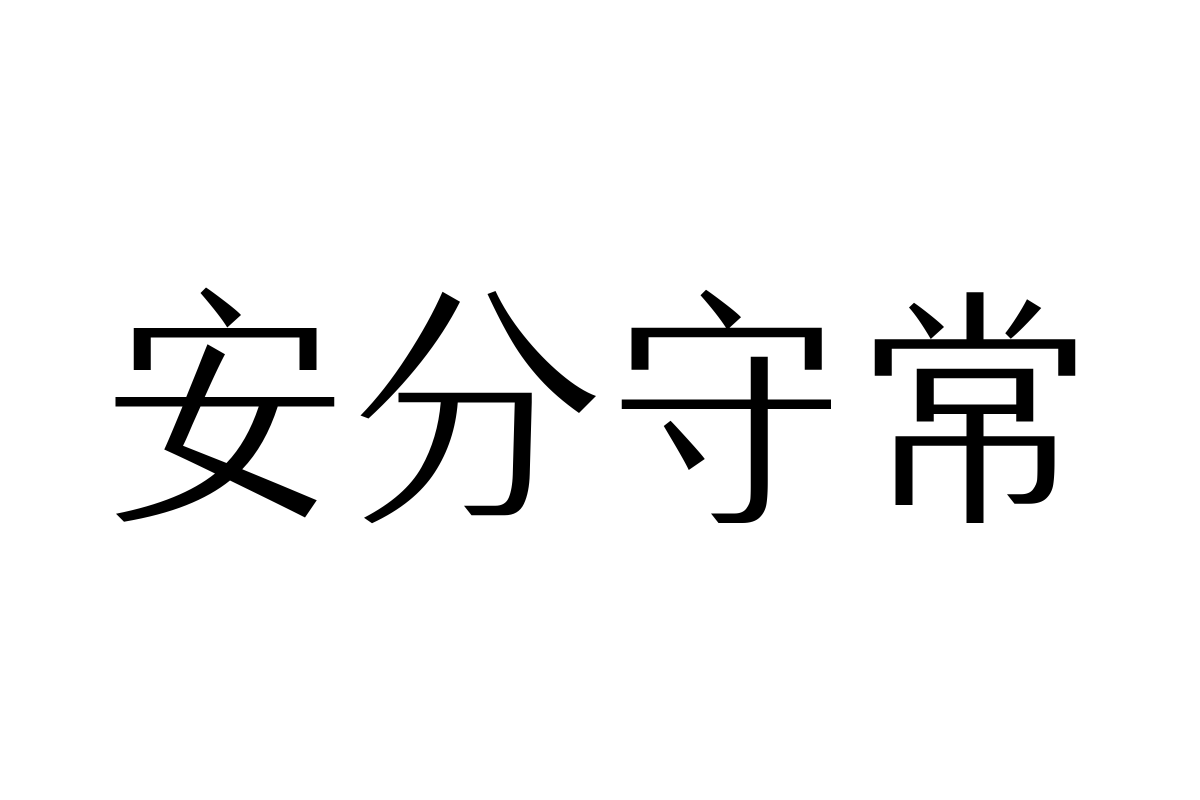
三极翰林简体字体是一款具有独特风格的中文字体,它采用了现代的设计元素,使得整体视觉效果更加简洁、大方。这款字体的特点主要体现在以下几个方面:
1. 字形优美:三极翰林简体字体的字形线条流畅,结构紧凑,给人一种优雅的感觉。无论是书写还是阅读,都能让人感受到一种舒适和愉悦。
2. 易于识别:这款字体的笔画粗细适中,易于识别,不会因为过于复杂而影响阅读效果。同时,它也具有一定的可读性,适合用于各种印刷品和电子屏幕上的展示。
3. 适用范围广泛:三极翰林简体字体适用于各种场合,无论是正式的文件、报告,还是日常的笔记、日记,都能轻松驾驭。它的设计既符合商务场合的需求,也能满足个人使用的需求。
总的来说,三极翰林简体字体是一款实用且美观的中文字体,无论是在办公、学习还是生活中,都能为你带来便利和美感。